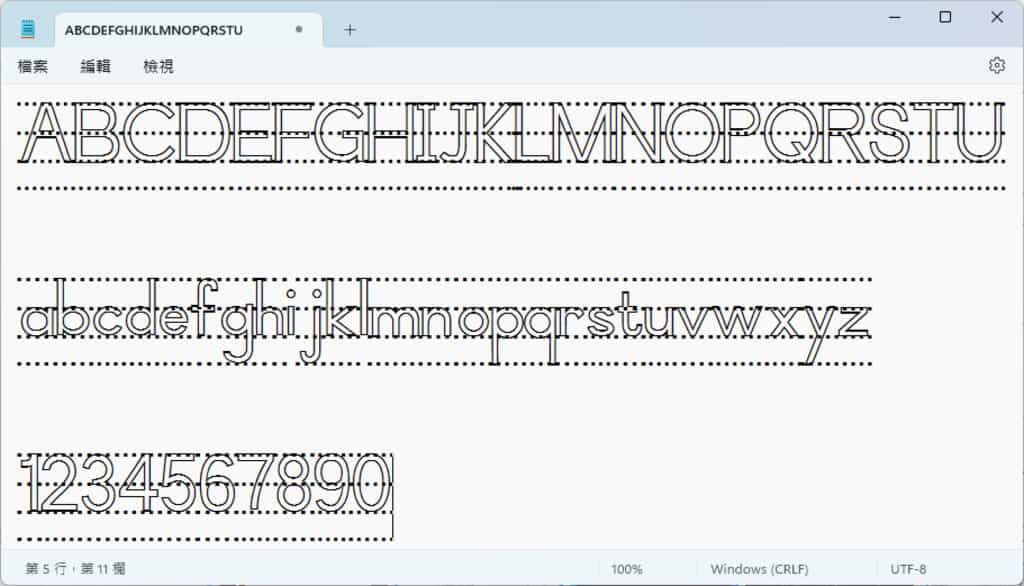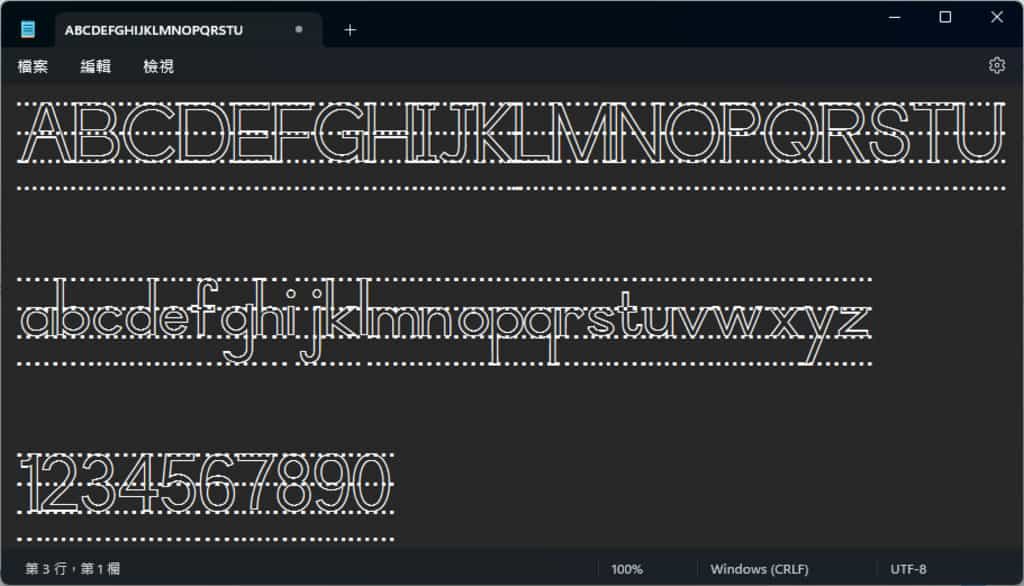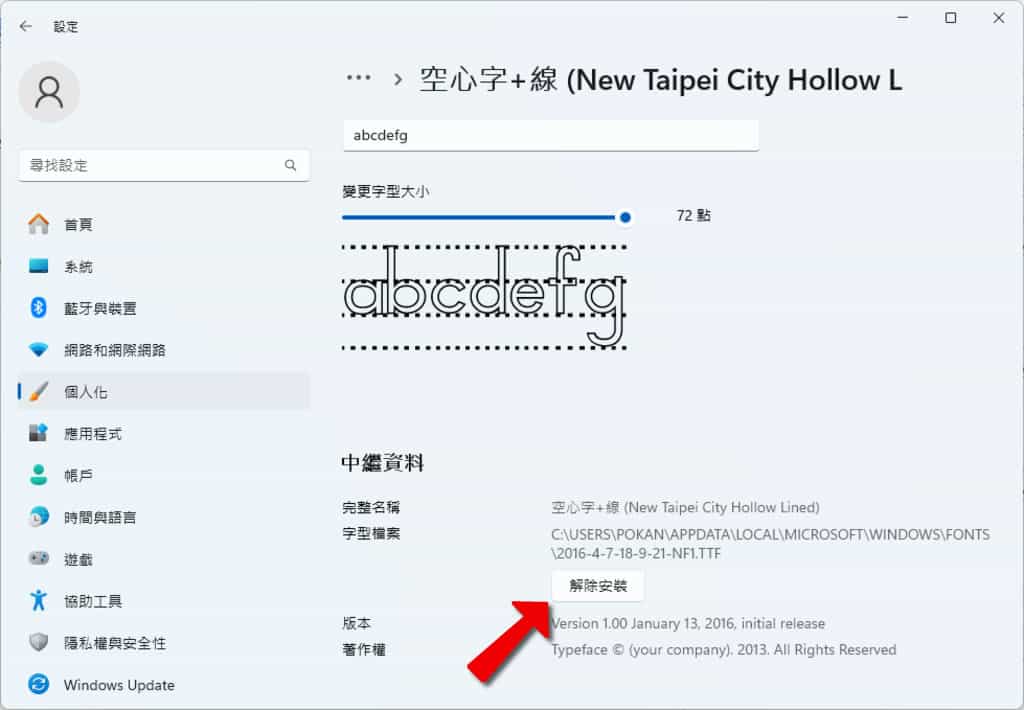
對於初學英文字母的小學生而言,通常都是靠著模仿的方式學寫字母,因此在作業中常見到搭配四線空白的點點字、空心字或實心字,藉此幫助初學者習得正確的字母書寫方式。市面上也有一些制式的作業簿提供使用。然而,若想要自行製作練習作業,新北市推出了自行研發的英文字母學習字型,包含「點點字」、「點點字+線」、「實心字」、「實心字+線」、「空心字」與「空心字+線」等六種字型供使用者選擇並安裝使用。這些特殊的字型設計有助於提升學生在課餘時學習英文字母的效果,進一步強化學習成果。